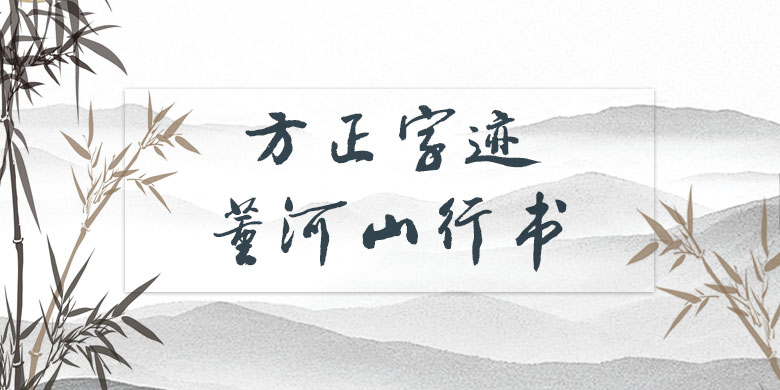
品牌:方正字迹设计师:董河山发行时间:2019字库编码:简繁扩展(GBK)、大陆简体(GB2312-80)分类:常规书写·毛笔字体属性:精品字
方正字迹-董河山行书取法晋唐笔意,融入欧楷,魏碑之长,传统功力深厚,笔力遒劲,刚健质朴,雅俗共赏,具有鲜明的艺术个性和时代感。作者董河山1985.9考入解放军艺术学院美术系,现为国家博物馆职业书画家。